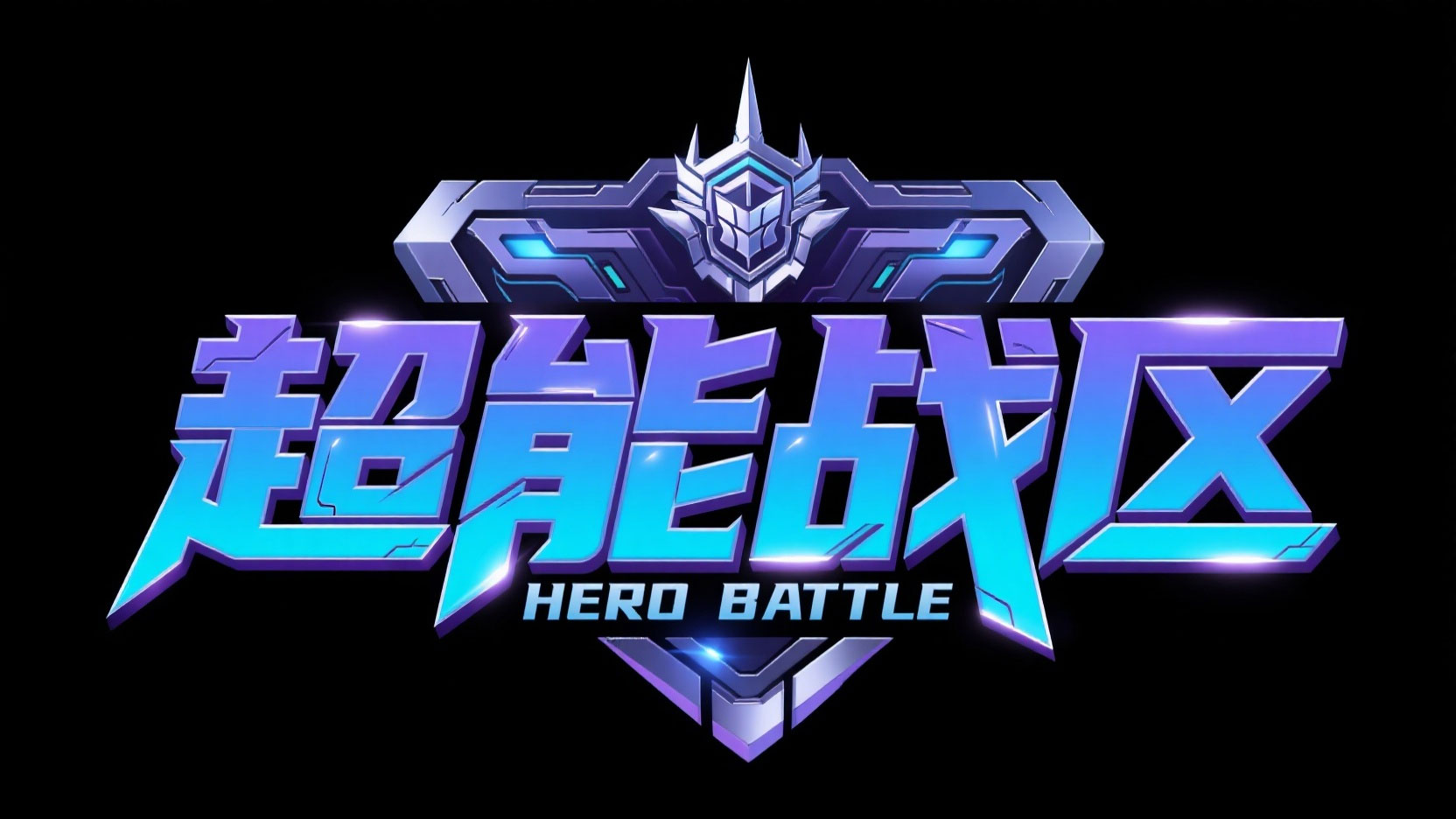
创作一个科幻机甲风锐利金属艺术字“超能战区” 采...
创作一个科幻机甲风锐利金属艺术字“超能战区” 采...AI字体提示词
风格定位
适合做风格探索与字形灵感延展。
适合场景
海报设计、品牌标题、电商设计、创意视觉
创作一个科幻机甲风锐利金属艺术字“超能战区” 采用蓝紫金属渐变,笔画锐利带机械切割感与高光;字形做机甲部件变形,融入顶部尖刺、中间徽章结构;英文 “HERO BATTLE” 匹配迷你机甲字体;标题整体突出未来战场的超现实战斗感 。文字与元素形成一个整体且为正视图,背景为干净的黑色。
可替换关键词
金属纸张肌理浮雕高对比立体阴影强笔触采用蓝紫金属渐变融入顶部尖刺“HEROBATTLE”
生成建议
• 先保留核心风格词,再替换材质、颜色和光影词做多轮尝试。
• 如果用于品牌标题字,补充品牌气质、行业属性和情绪关键词。
• 如果用于海报或电商标题,额外强调大字、对比度和视觉冲击力。